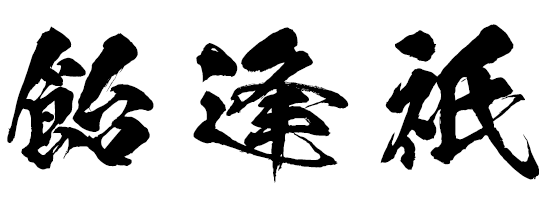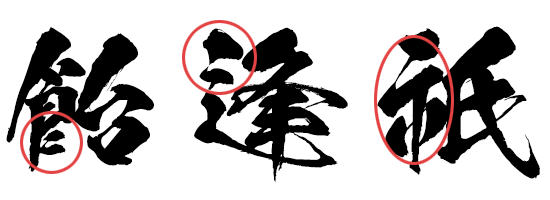
昭和書体 高解像度毛筆書体「闘龍」
昭和書体が作り出す表情豊かな毛筆文字は、印刷物のみならず、ゲームやアニメの世界でも幅広く利用されており、デザイナーやクリエイターにとって欠かせない存在といっても過言ではありません。その中でも「闘龍」は、アニメ「銀魂」「鬼滅の刃」でも採用された毛筆書体。闘争心にあふれ、力がありあまった若い龍が空を舞うさまをイメージして作られ、拡大して使うほどに迫力が増す「かすれ」を存分に活かした、昭和書体を代表する人気書体です。
昭和書体の特徴
闘龍の特徴 〜 毛筆ならではの文字の掠れ
細部まで再現された、とめ はね はらい
筆文字の掠れは、文字の魂が紡ぎ出す独特の美しさと、微妙な揺らぎや細かな変化が文字に立体感や動きを与えます。「闘龍」は、端正な文字にはない、わずかな乱れや曲線の揺れや、力強い筆の運びによって生み出された大胆な掠れを丁寧に作られた書体です。
アウトライン化したときのアンカーポイント
「闘龍」の輪郭線の拡大図と、アンカーポイントを示した図です。
昭和書体の高解像度書体はアンカーポイントが非常に多く、とめ・跳ね・払いや毛筆らしい“かすれ”など、細部の再現性が非常に高くなっています。
闘龍の魅力 〜 JIS90/JIS2004が選べる
闘龍では、従来から広く利用されてきたJIS90規格の「闘龍」の他、近年主流となりつつあるJIS2004規格の「闘龍N」もラインナップされています。
両規格では漢字のうち168字の例示字形が若干異なっており、概ねJIS90字形のほうが略字風、JIS2004字形のほうは正字・旧字風のデザインになっています。
JIS90/JIS2004で字形が異なる文字の例
JIS90字形
闘龍
JIS2004字形
闘龍N
NなしとN付きの字形差 (JIS90・JIS2004で例示字形が異なる文字の一覧)
JIS90規格とJIS2004規格で例示字形が異なる168文字のうち、シリーズ収録範囲に含まれる167文字を「闘龍」「闘龍N」で比較した一覧です。
(毛筆書体の特性上、明朝体やゴシック体ほどには字形差がはっきりしない文字もあります。)
文字サンプル
闘龍の使用例